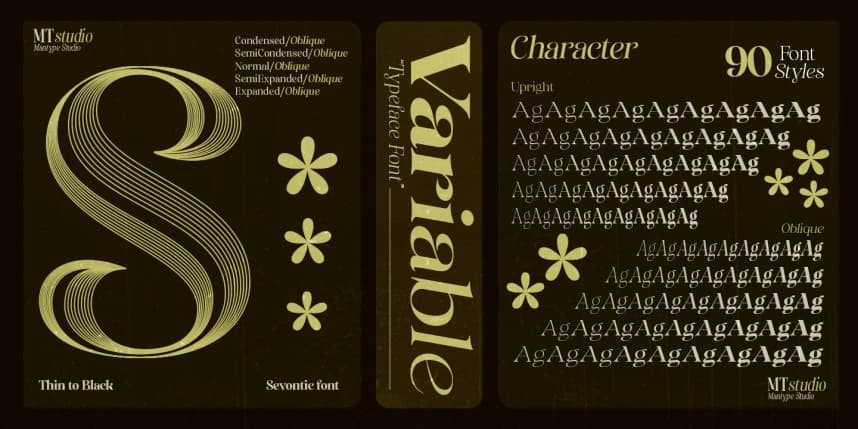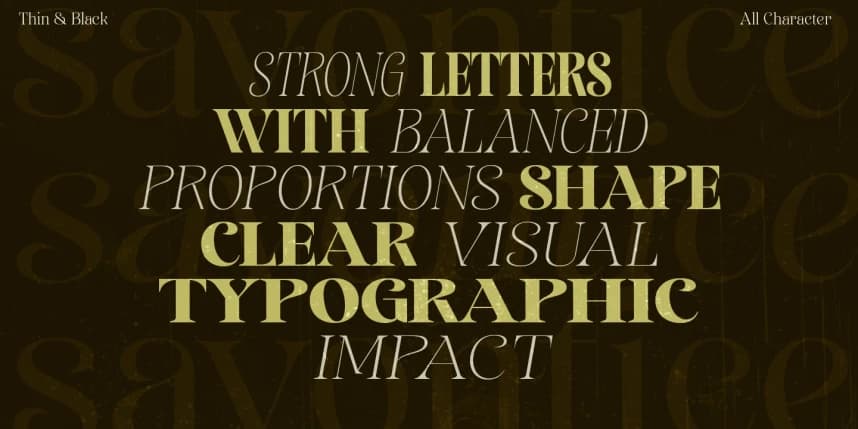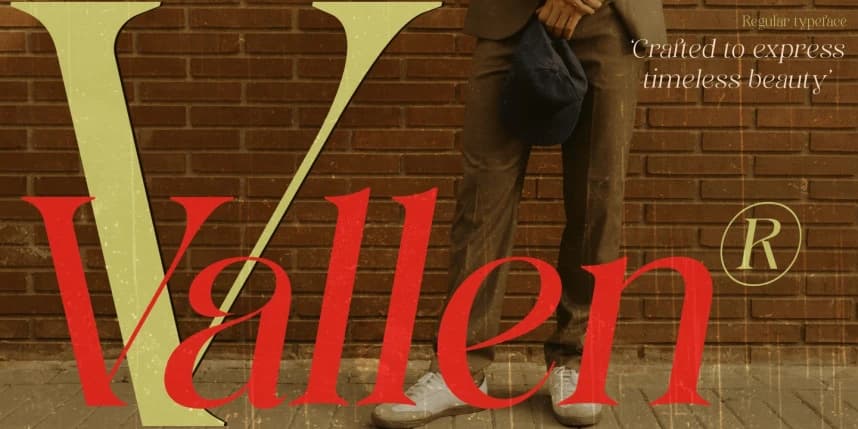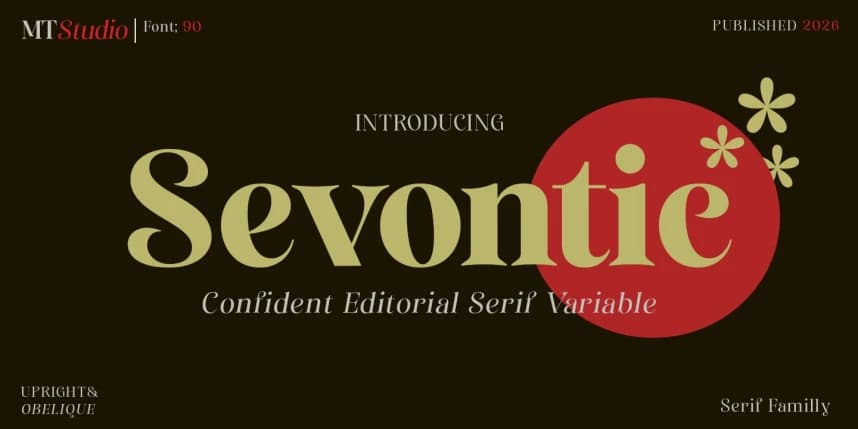
Sevontic Font
Savontie Font, güçlü fakat zarif bir karaktere sahip bir serif yazı tipidir. Kalın ve ince hatlar arasında belirgin bir kontrast sunar; bu da güven veren, klasik ve sofistike bir izlenim yaratır. Pürüzsüz ve kontrollü serifler, üst düzey bir nüans katar.
Savontie Font, güçlü ama zarif bir karaktere sahip bir serif yazı tipidir. Kalın ve ince çizgiler arasındaki belirgin kontrast sayesinde kendinden emin, klasik ve sofistike bir etki yaratır. Pürüzsüz ve kontrollü serifler ise premium bir nüans katar.